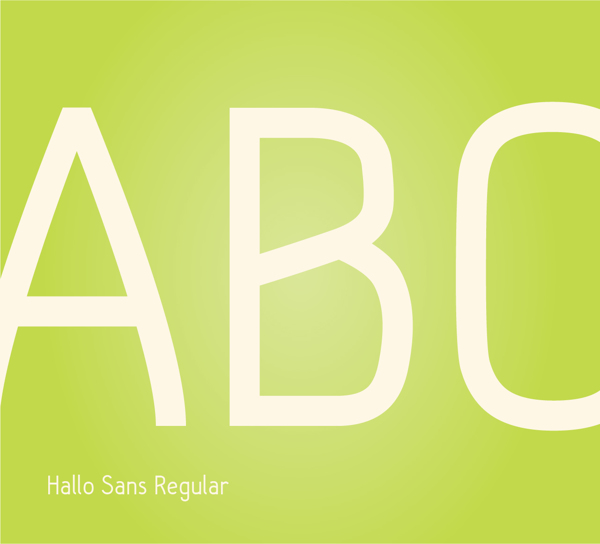
Acabó otra semana más y ya van nada menos que doce, el tiempo vuela! Pero con el fin de semana llega la tipografía de los viernes. En este caso una san serif muy cuidada, perfecta para su uso en cabeceras y pequeños textos disponible en tres pesos diferentes y con licencia libre. La podréis utilizar tanto en proyectos comerciales como en trabajos personales. Su autor, Fredrik Staurland de Oslo tiene también un fantástico portfolio que recomendamos totalmente que visitéis. Espero que os guste y recordad que los like y los follow ayudan mucho así que visitadnos en Twitter y Facebook. También nos podéis encontrar en Flipboard buscando nuestra revista El Arquitecto de Ilusiones.